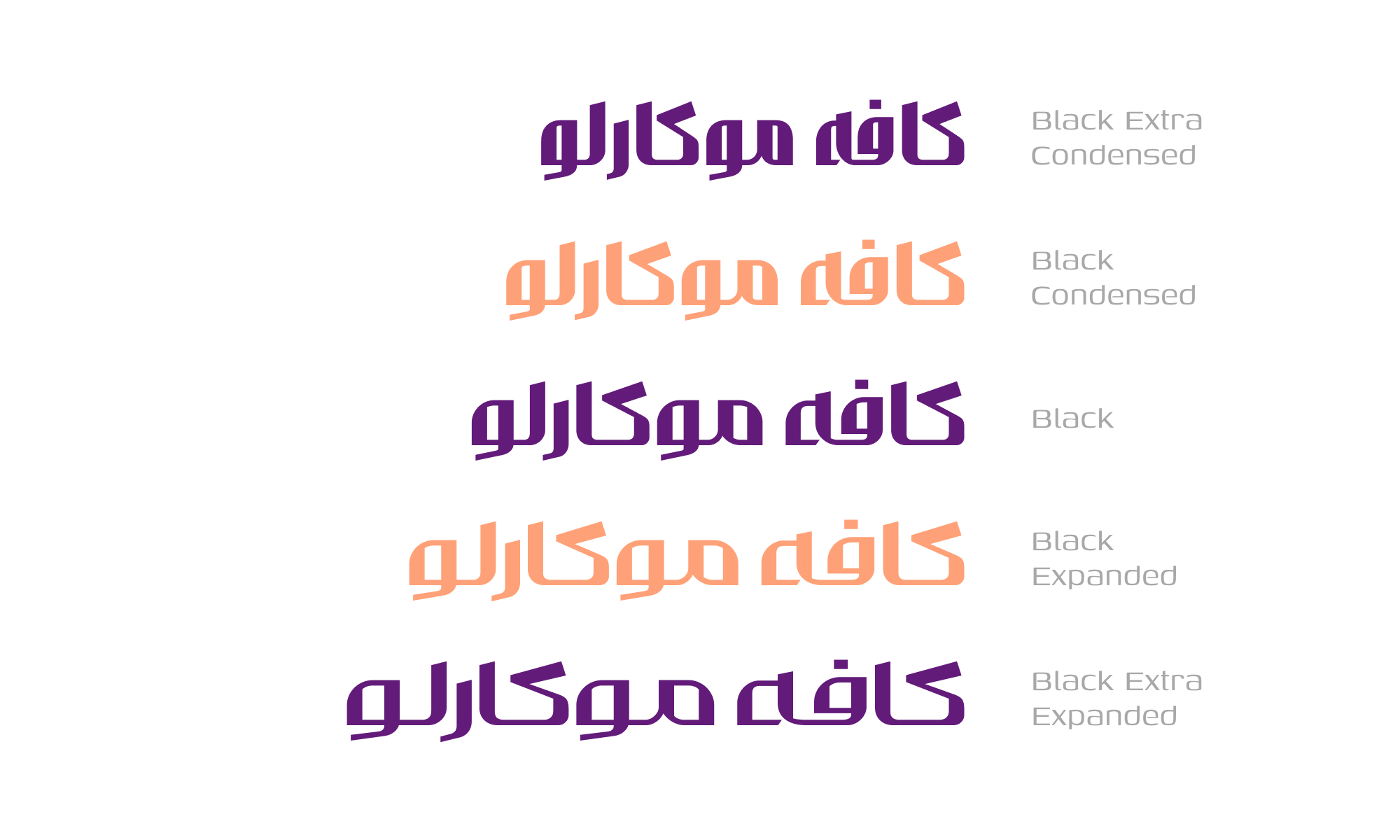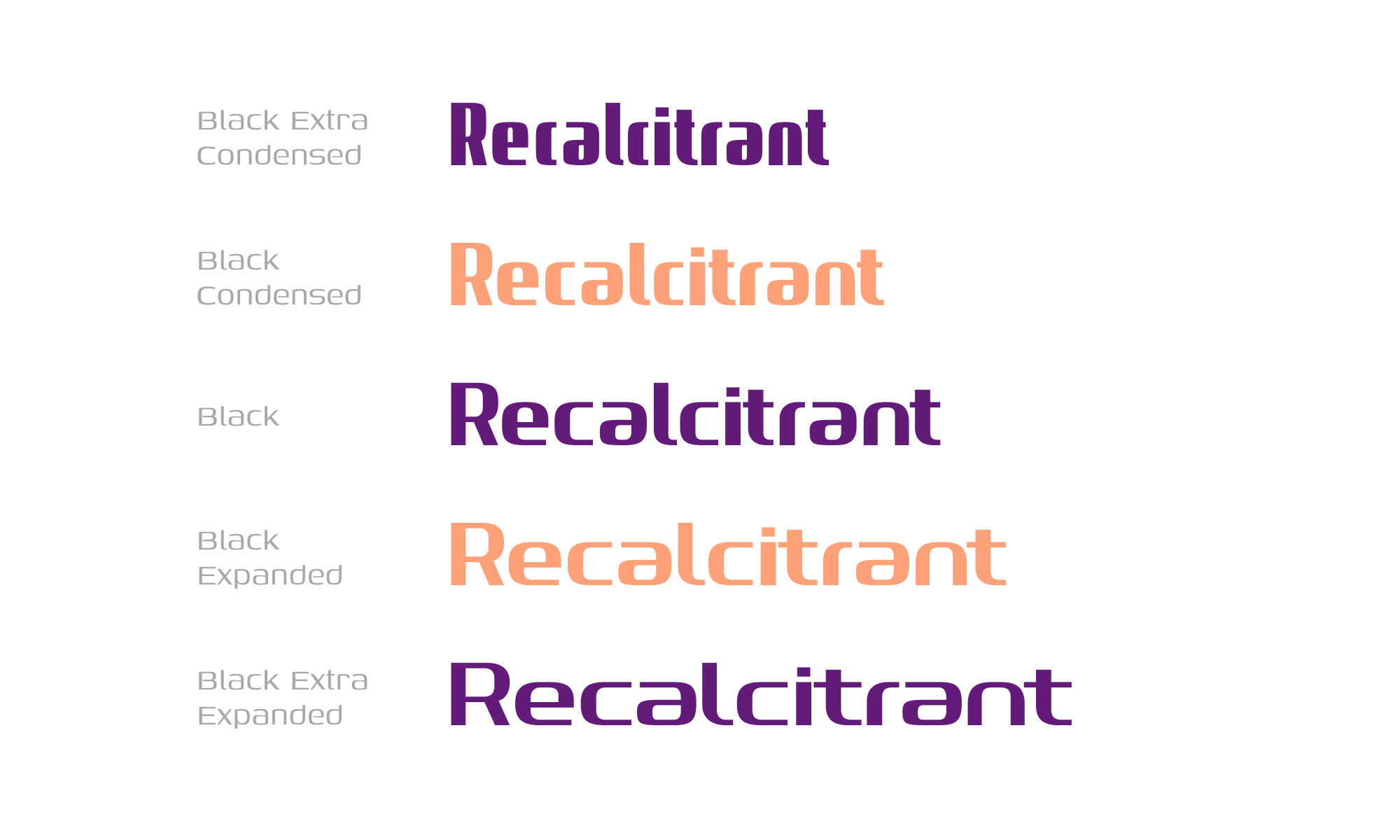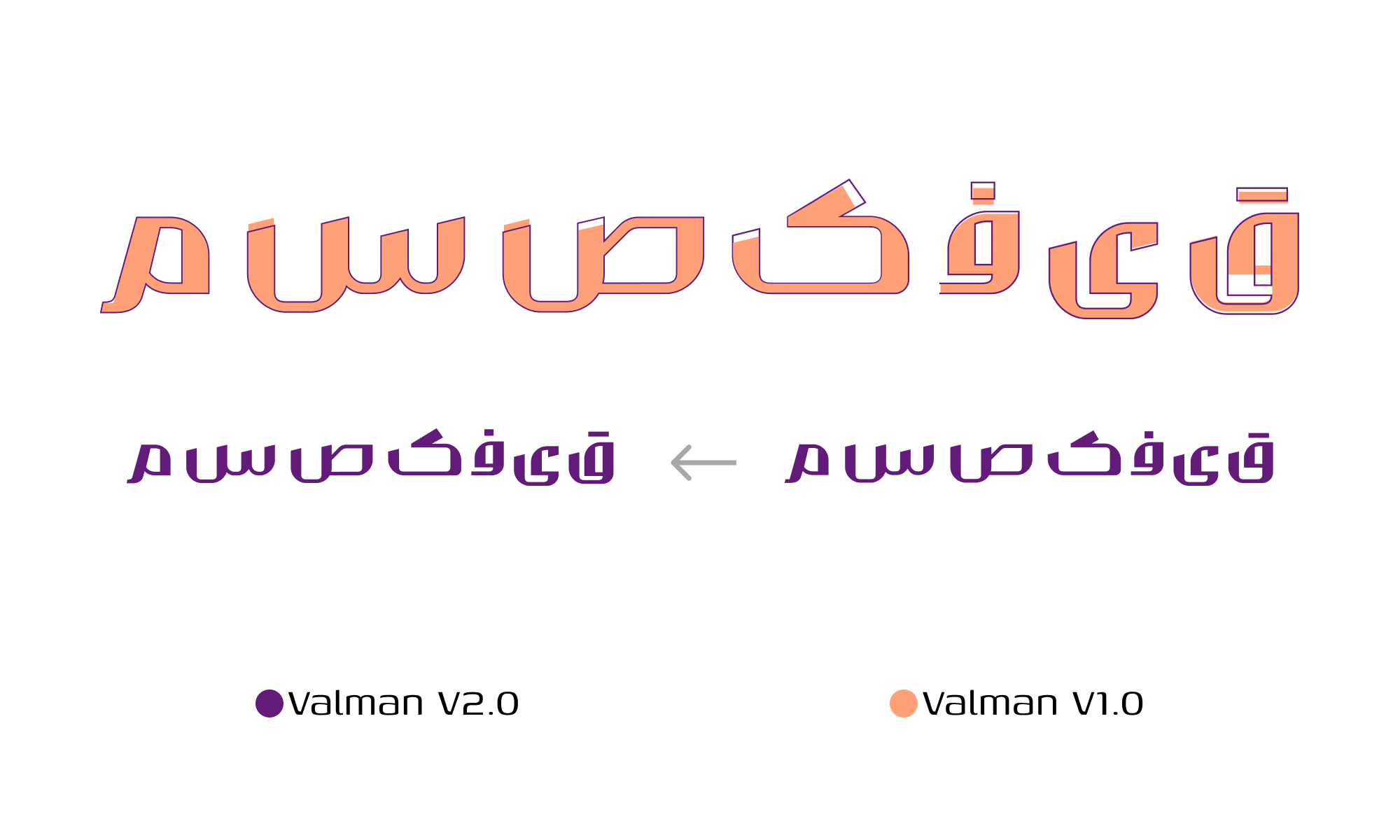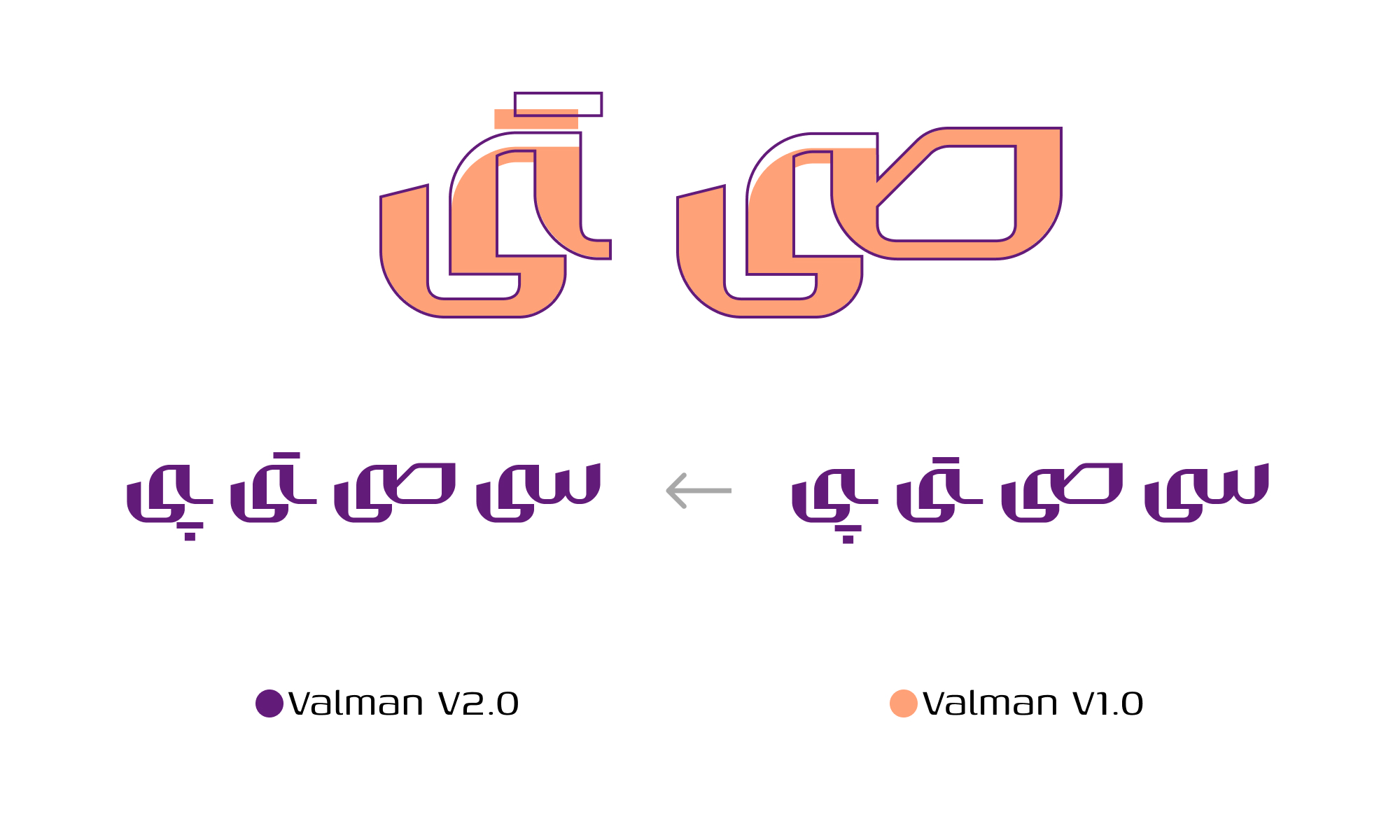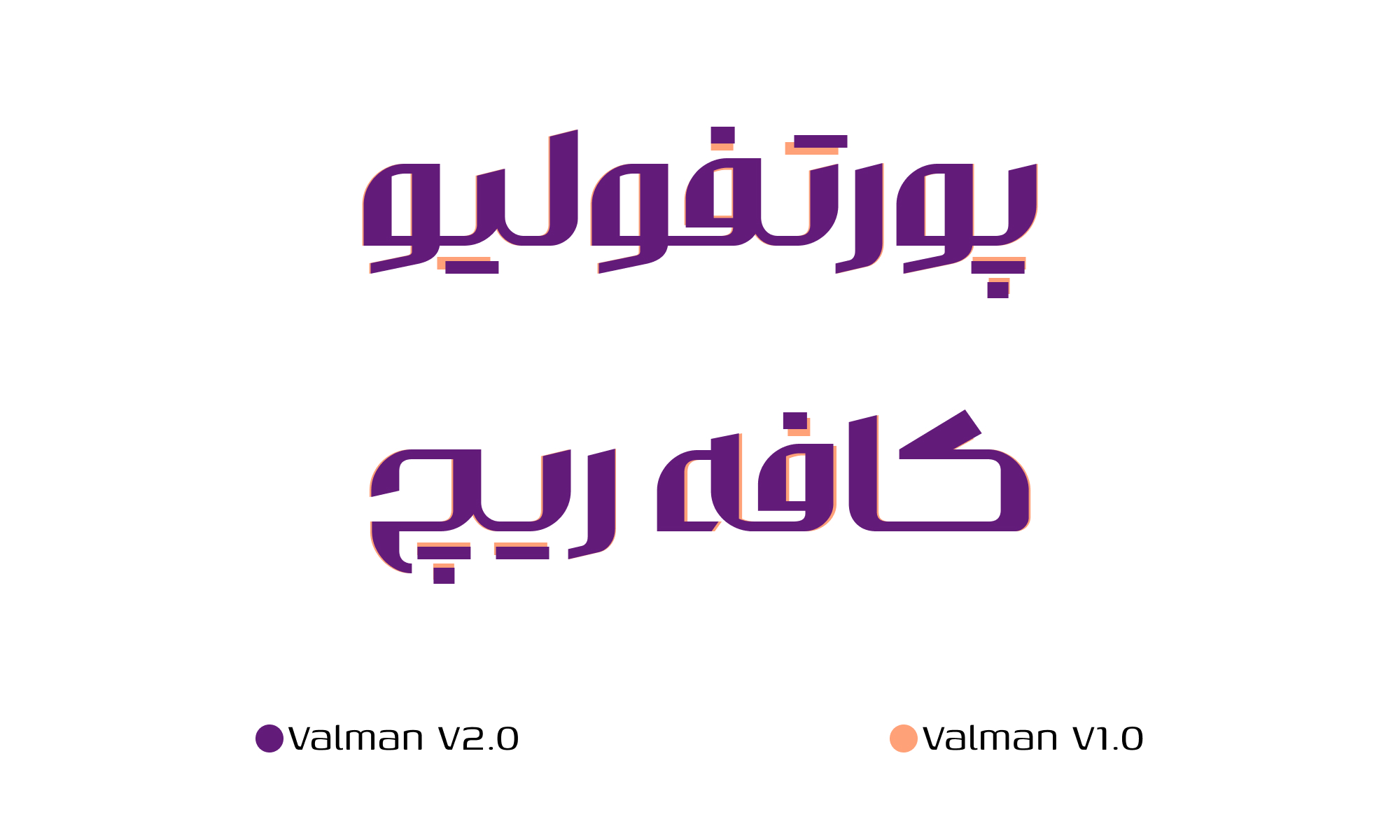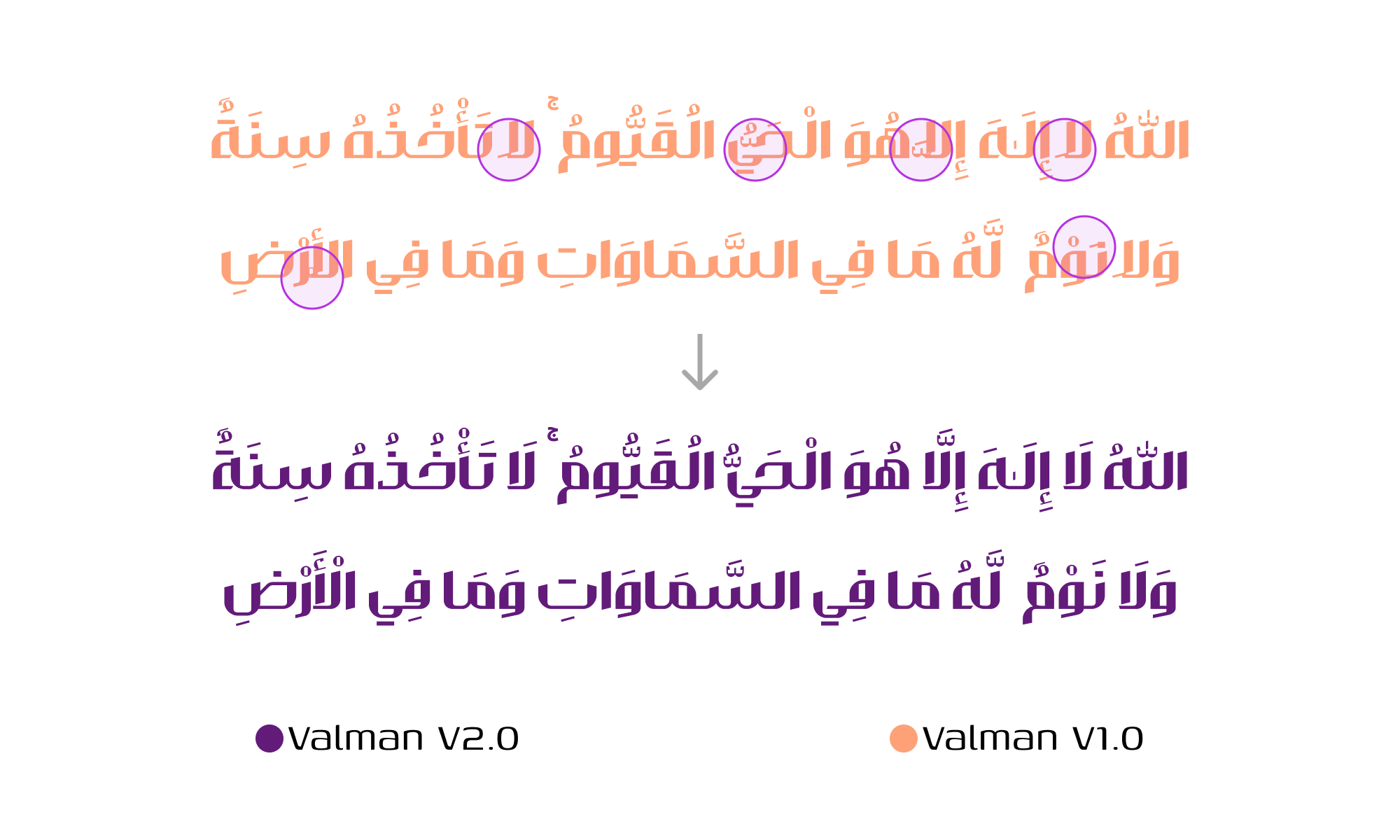
در نسخهی ۲ فونت والمان چه تغییراتی میبینیم؟
۱. سبکهای ExtraCondensed, Expanded, ExtraExpanded برای فونت طراحی شد و حالا فونت والمان دارای ۵ سطح عرضی + وریبل فونت است.
۲. حروف، اعداد و علائم انگلیسی بهصورت اختصاصی و همآهنگ با کاراکترهای فونت والمان طراحی شد.
۳. فرم برخی حروف اصلاح و بازطراحی شد.
۴. فرم برخی از ترکیبات بازطراحی شد.
۵. محل قرارگیری نقاط بهطور کلی بازبینی شد.
۶. اعرابگذاری بهطور کلی بازبینی و اصلاح شد.